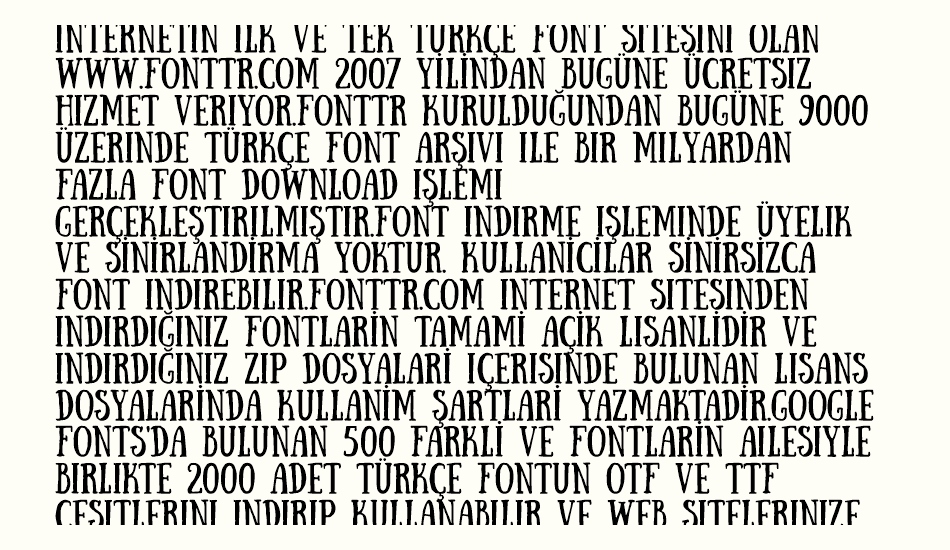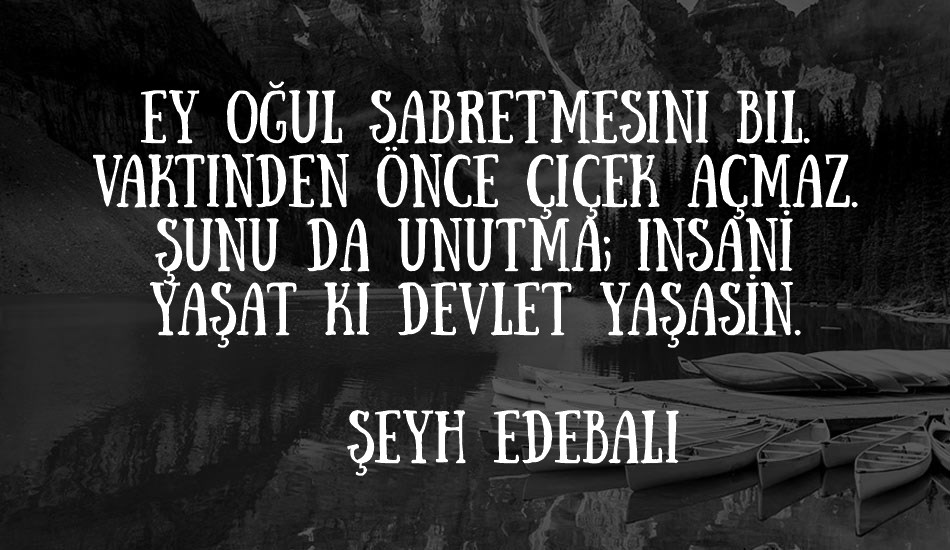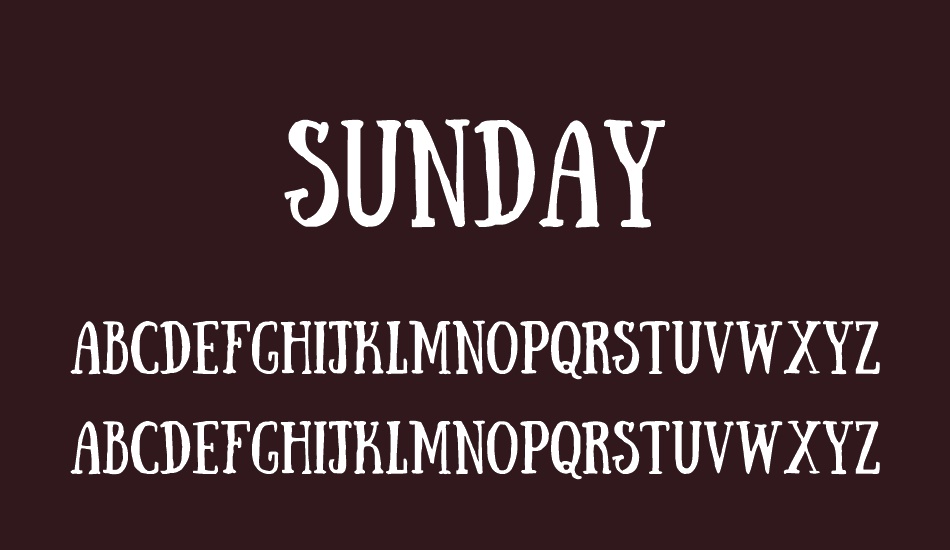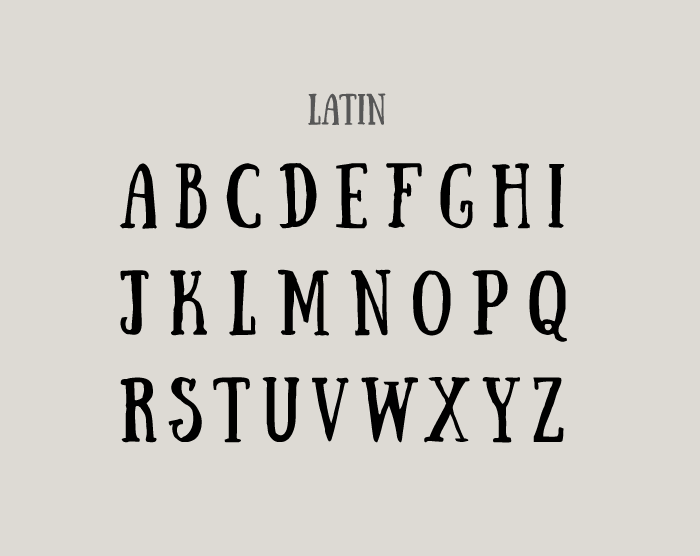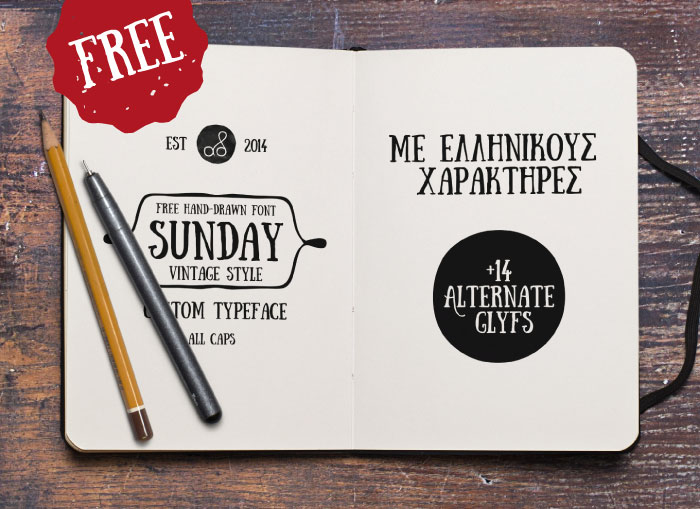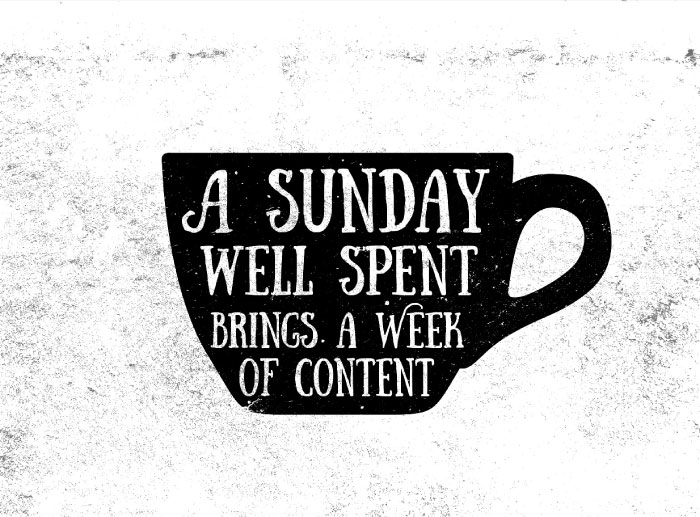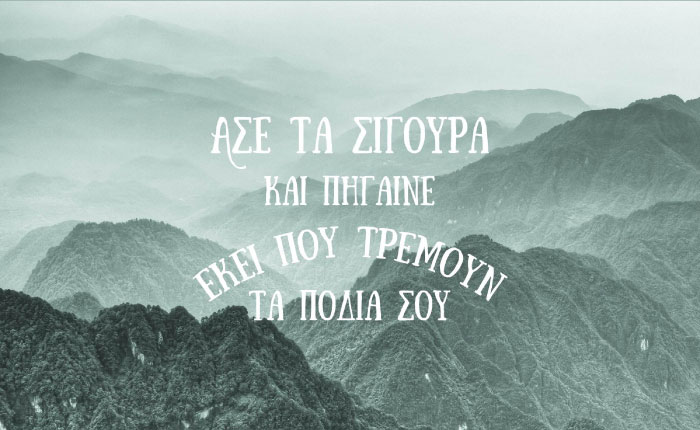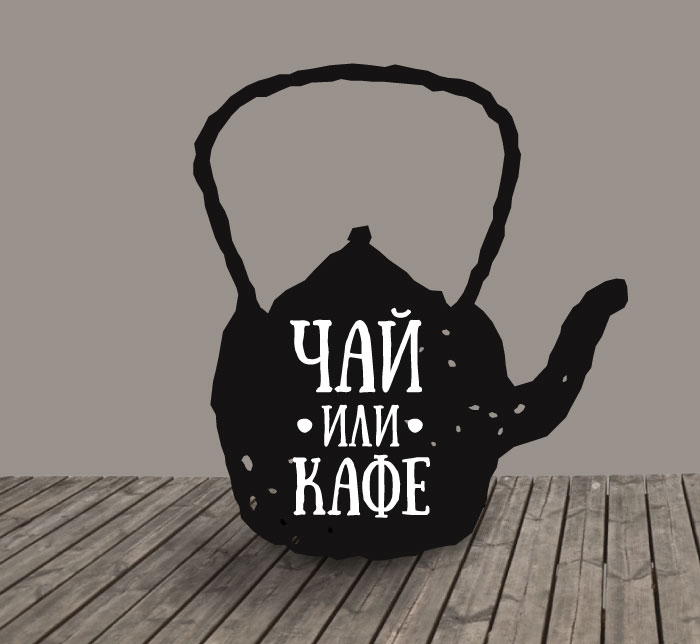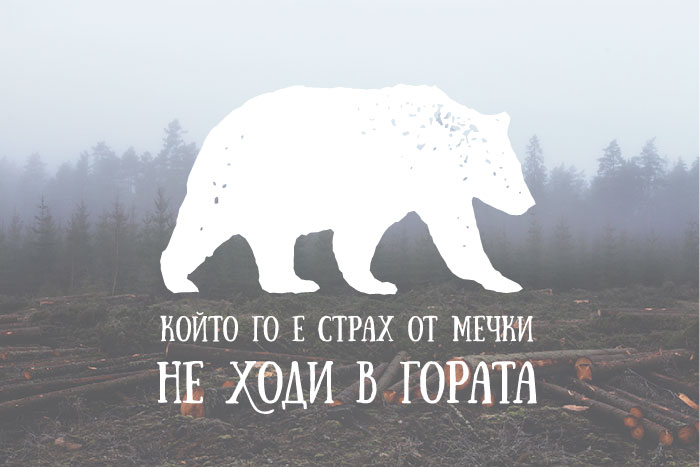
Sunday font
Anastasia'nın bu yazı tipinin ardındaki kısa bir hikaye: Ben illüstrasyonu ve mektupları hep sevdim, ancak ikisi de "yasak meyveler" idi. Asla bir gün bir illüstrasyon veya mektup formu formatı oluşturabilirdim. Ve hayal edebileceğim en son şey bir yazı tipi tasarlamak! Yazı yazmaya başladığımdan bu yana neredeyse bir yıl geçti ve sadece eski ve eski el yazılarını keşfettiğimden bu yana sadece birkaç ay geçti. Hemen aşık oldum ve çok çalışmaya karar verdim. Geçen pazar, uygulamanın bir parçası olarak, kendi özel yazı karakterimemi kullanarak logolarımı eski tarzda yeniden tasarlayabileceğimi düşündüm.